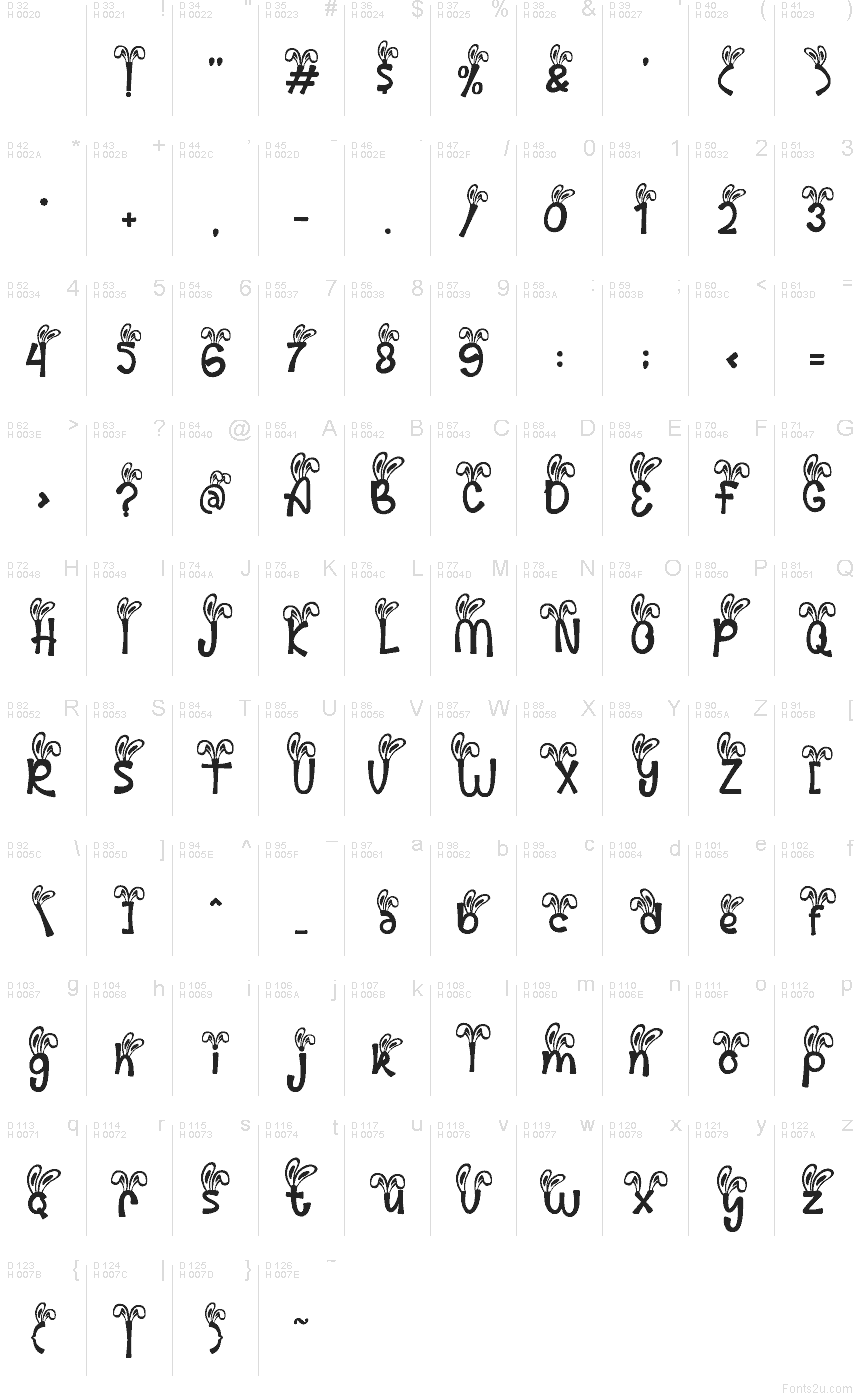
Palm Sunday Bunny Ear
La tipografía Palm Sunday Bunny Ear de Putracetol Studio es una fuente display gratuita para Pascua. Sus letras altas están coronadas con formas de orejas de conejo que le dan un toque estacional a cada carácter. Los trazos se mantienen sencillos y redondeados, convirtiendo el alfabeto en un conjunto decorativo temático sin añadir desorden visual.
Palm Sunday Bunny Ear es una fuente gratuita ideal para tarjetas de Pascua, carteles de primavera, invitaciones a eventos, etiquetas de tiendas y gráficos festivos en redes sociales. Sus formas temáticas también resultan útiles para titulares decorativos, etiquetas de temporada y empaques artesanales cuando buscas que la letra sea la protagonista del motivo festivo.